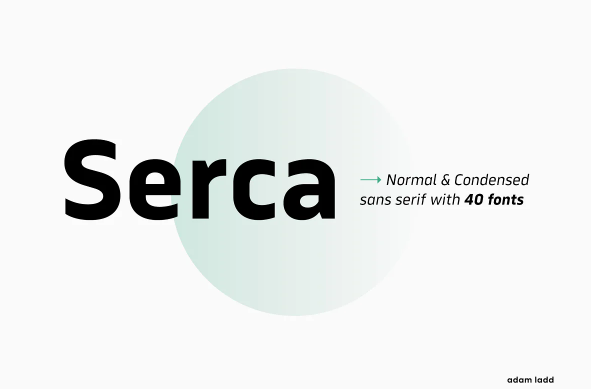
Serca - это структурированное геометрическое семейство шрифтов sans serif с нормальными и сжатыми пропорциями. Он профессиональный и точный, открытый и разборчивый. Современный, чистый дизайн позволяет использовать его в различных областях - брендинге, рекламе, веб-сайтах, мобильных приложениях, логотипах, журналах и т.д. - как в мелком основном тексте, так и в крупных заголовках.
Характерными чертами дизайна являются вертикальные клеммы, открытые отверстия, большая высота x и наклонные стебли в местах соединения кривых. Для большего типографского интереса или экономии места сочетайте обычный и сокращенный стили вместе. Широкий диапазон начертаний - от тонкого до черного с курсивом - дает множество вариантов для выбора (также включает начертание Text для немного более темного вида, чем Regular).